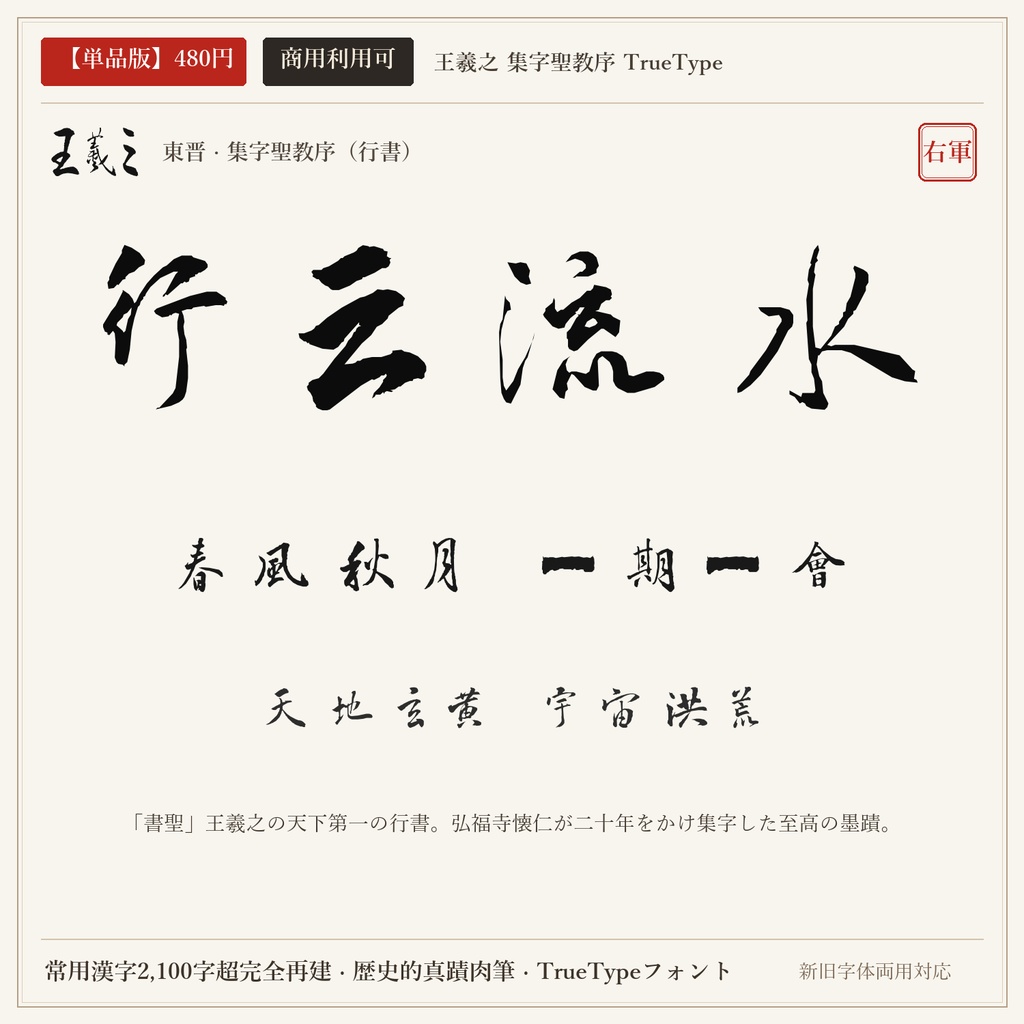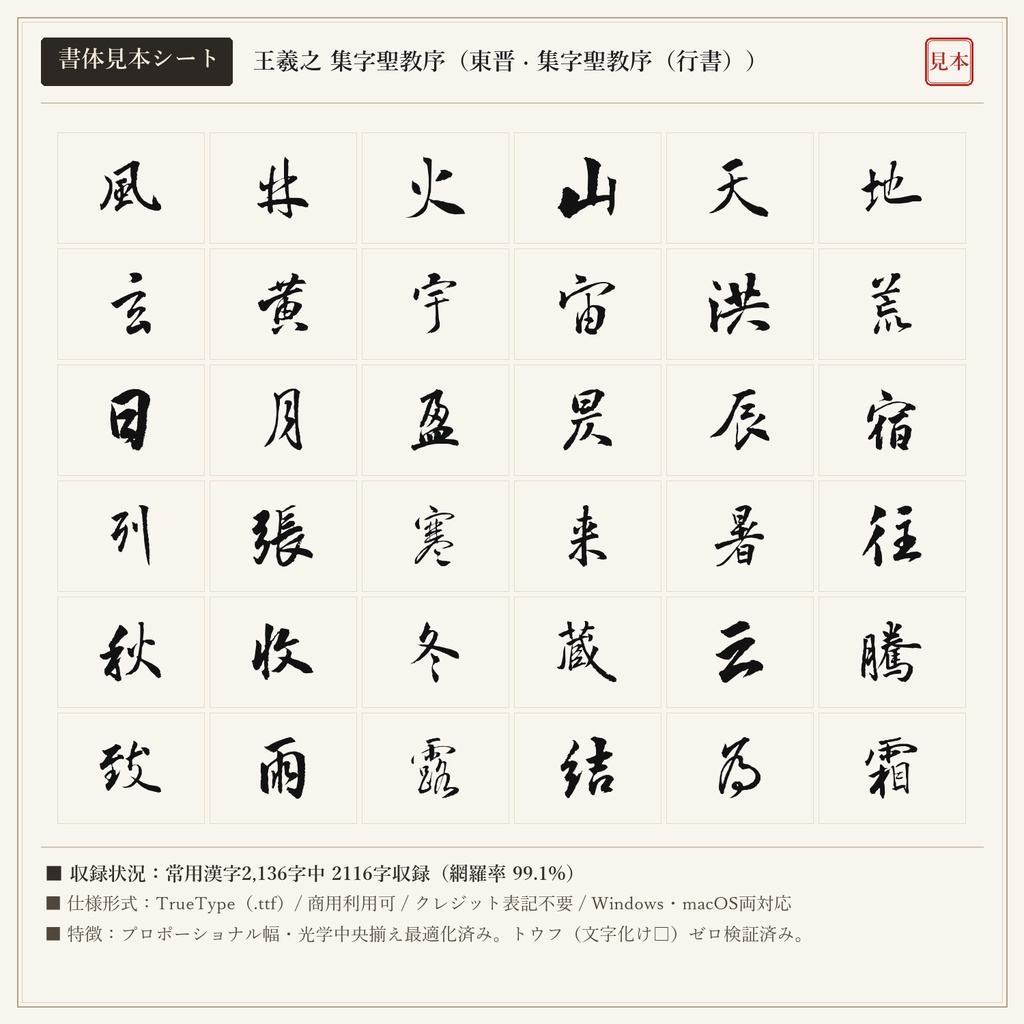
中国三千年の書道史において頂点に君臨する「書聖」王羲之の真蹟から、唐代の僧・懐仁が20余年を費やして集成した『大唐三蔵聖教序』を忠実にTrueType化したフォントです。神妙にして変幻自在の筆勢を誇ります。 ■ 本フォントの特徴 ・常用漢字2,136字中、2116字を高精度収録(網羅率 99.1%)。 ・現代の新字体を入力しても、歴史的な真蹟字形・旧字体が自然に出力されるデュアルマッピング対応。 ・文字ごとの最適なプロポーショナル字幅設定により、自然で流麗な連綿と墨の息遣いを再現。 ・トウフ(文字化け□)を出さない事前フォントマッピング検証済み。 ■ 未収録文字一覧(全20字) 歴史的真蹟・拓本に存在しない以下の字種は未収録(非対応)となります。ご購入前にご確認ください。 丼 刹 咲 唄 堀 峠 拶 枠 栃 桁 濫 疎 線 脊 菓 著 込 郷 闘 駄 ■ 形式 TrueTypeフォント(TTF) / Windows・macOS両対応 ■ 利用規約 個人・法人の商用利用OK。クレジット表記不要。 ロゴ、動画、ゲーム、書籍、同人誌、配信サムネイル、Web、印刷物、グッズ等に自由にご使用いただけます。 フォントファイル自体の再配布・共有・販売・転売は禁止です。 ※東晋の王羲之(行書)と盛唐の顔真卿(楷書)を同梱した「【無料版】王羲之 + 顔真卿 2書体セット(0円)」もショップ内にて無料配布中です。